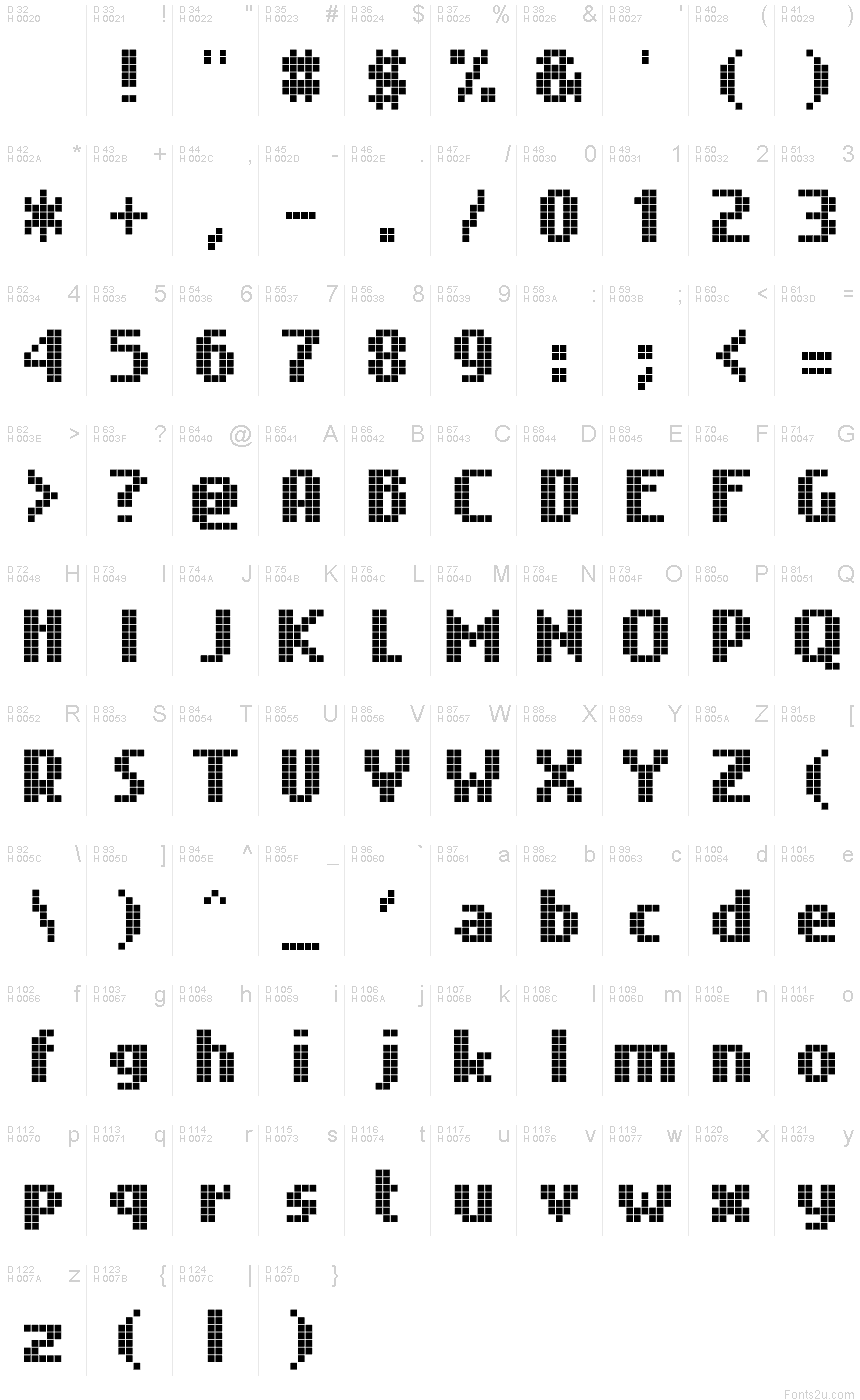
Nokian od czcionki.com je bezplatné pixelové písmo typu display, které vychází z přísné mřížky čtvercových modulů. Tato opakující se bloková struktura dodává písmenům vzhled displeje telefonu nebo výsledkové tabule, přičemž odstupňované hrany a pravouhlé mezery zůstávají v celém designu konzistentní a nepůsobí jako náhodné zkreslení.
Krátké popisky, herní menu, návrhy aplikací, titulky na plakátech a letáky s technickou tematikou zde dávají smysl, protože toto písmo udržuje každé slovo v rytmu ostrých dlaždic. Dokáže také skvěle ukotvit ziny nebo merchandising, které chtějí odkazovat na rané mobilní nebo nízkorychlostní digitální formáty, aniž by sklouzly k měkčímu arkádovému písmu nebo zaoblenému sci-fi stylu.
Nokian